MdNデザイナーズファイル2025
インプレスグループでデザイン分野のメディア事業を手がけるエムディエヌコーポレーションは、自分のデザイン・表現を生み出すためのヒントが詰まった最新デザイン年鑑『MdNデザイナーズファイル2025』を発売した。
Nデザイナーズファイル2025』は創刊から23年を迎えるデザイン年鑑。
「広告」「シンボル&ロゴタイプ」「装丁」「エディトリアル」「パッケージ」「グッズ」「Web」「UI」の8つのジャンルで、最先端を切り拓くトップクリエイター&新時代を担う若手デザイナー、256組の最新ポートフォリオとプロフィールデータを収録している。
2025年度版はアートディレクションを装丁家・書体デザイナーの山田和寛氏(Nipponia)が手掛けた。
クラフト紙を使用したカバーデザインは、「ずっとあるものと、新しいものの融合」をテーマに、金属活字の清刷りと3DCGを用いて表現したものとのこと。
『MdNデザイナーズファイル2025』に掲載されている多種多様な作品を通して、デザインの潮流が見渡せると同時に、創作のインスピレーションも刺激されるはず。
現役のデザイナーとして活躍されている人はもちろん、商品や広告のデザイン・ブランディングを依頼する方、クリエイティブ業界を志す方などにも必携の1冊となる。
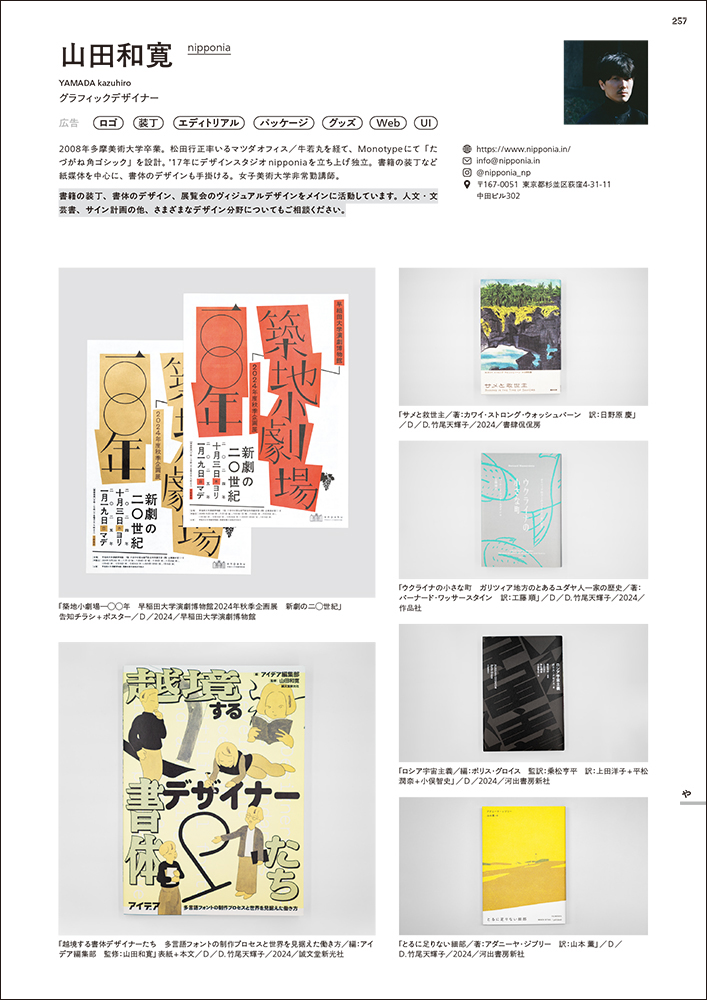
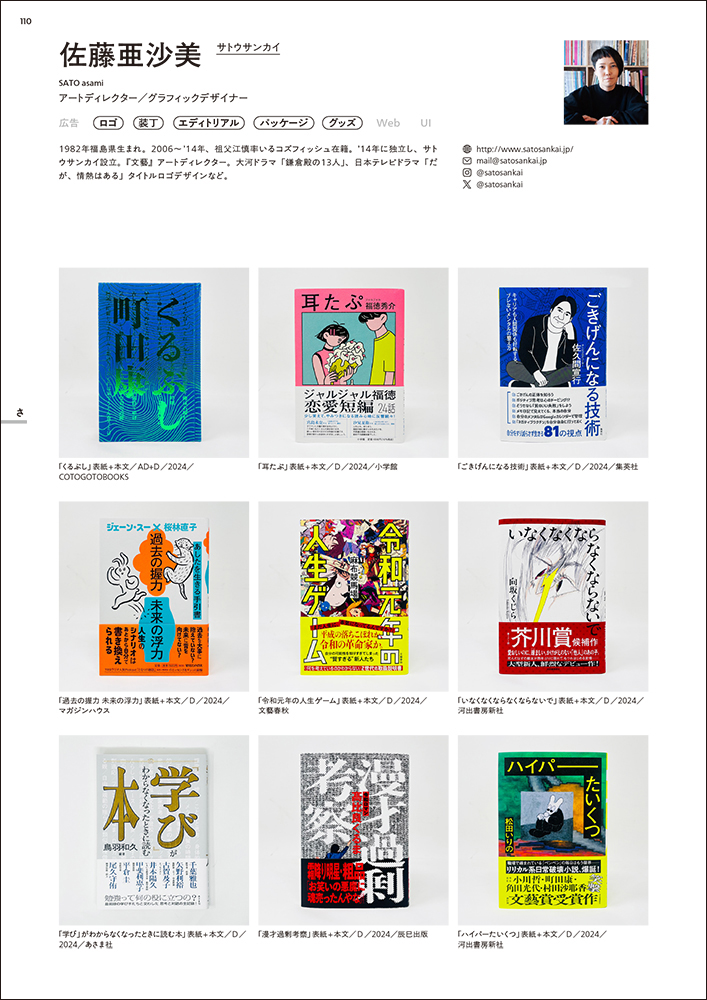
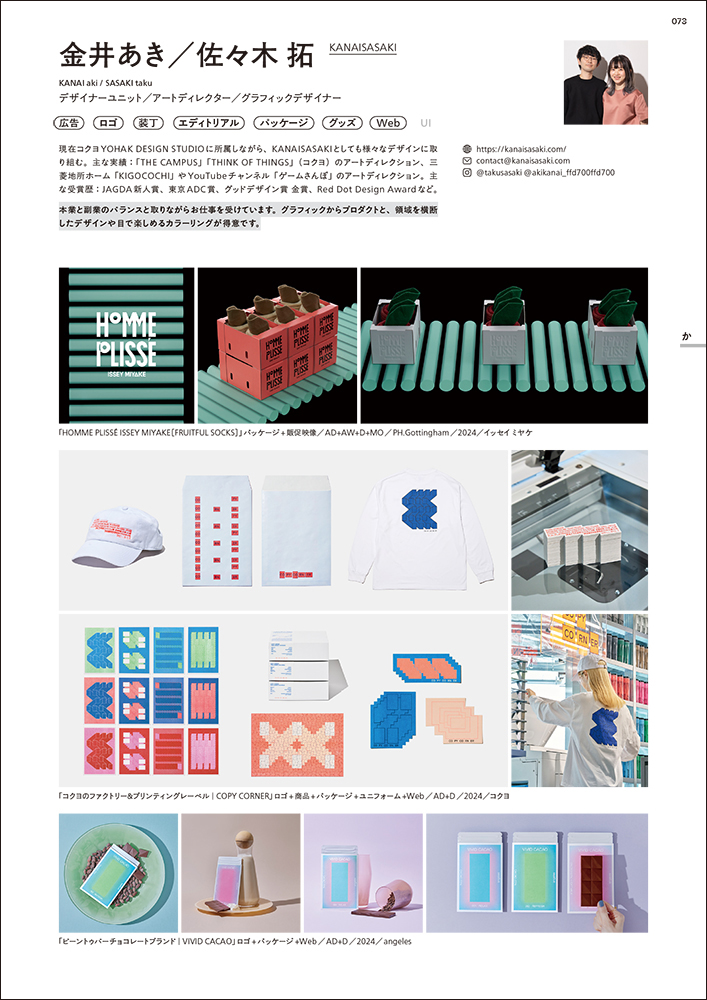
『MdNデザイナーズファイル2025』対象読者
○最新のグラフィックデザインの潮流を知りたい人
○広告宣伝、商品の企画開発、広報などに関わる人
○デザイン業界やクリエイティブ業界を志す人
『MdNデザイナーズファイル2025』の掲載者(抜粋・敬称略)
青栁 徹(あを)/青山希望(non Editions)/赤井佑輔(paragram)/浅岡敬太(Dentsu Creative Pictures)/新井大輔(装幀新井)/荒川 敬(BRANDING DESIGN BRIGHT)/有馬トモユキ(日本デザインセンター ポリローグ研究室)/ARENCE/安藤真理(marii)/安藤陽介/飯塚よしみ(ANDRICE Inc.)/ium inc.(小玉千陽)/五十嵐祐太(adhouse public)/池越顕尋(GWG inc.)/石川知弥/石原絵梨/泉 美菜子(PINHOLE)/一森加奈子/出井ゆみ/伊藤佑也(83graphics)/稲垣小雪/井上麻那巳(Troublemakers Publishing)/上浦智宏(design office ubusuna)/上杉 滝|上杉 咲(Knot for, Inc.)/江副哲哉(あおいろデザイン)/江連有美(TSDO Inc.)/江波戸李生/大内かよ(OKデザイン室)/大﨑奏矢/大澤悠大/大島慶一郎/大瀧由子(大瀧デザイン)/大坪メイ/大西隆介(direction Q inc.)/大原漢太郎/大東浩司(AD FAHREN) ほか多数掲載